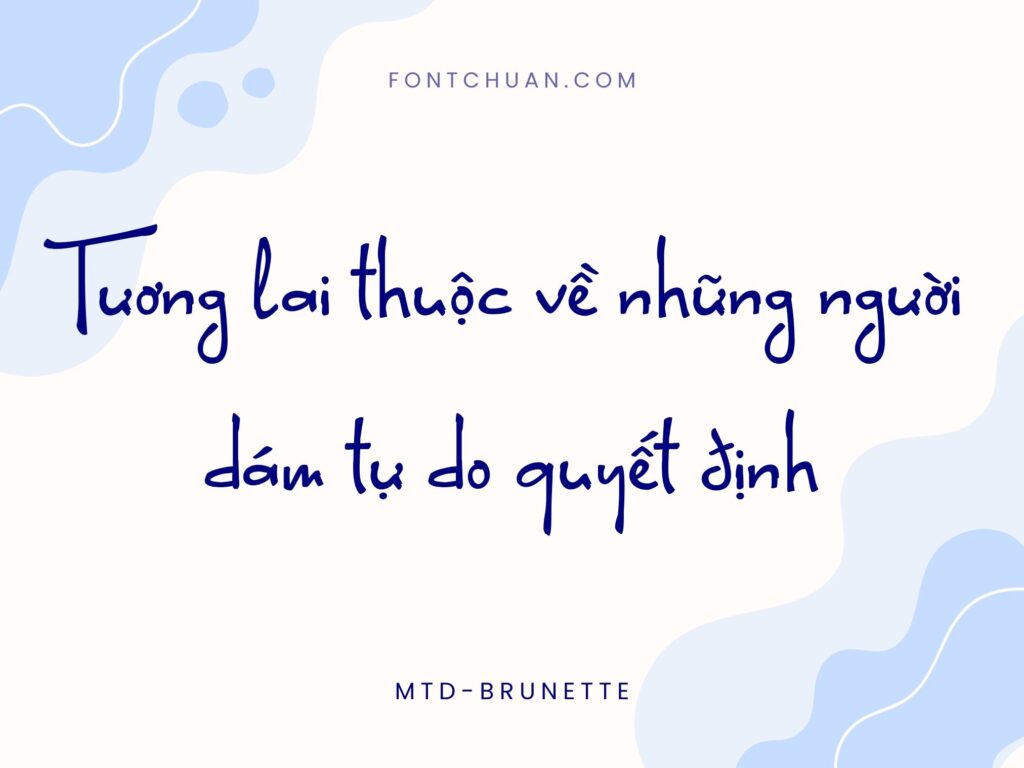
Font MTD Brunette Việt Hóa
Tác giả Font: Deartype
Font MTD Brunette là một kiểu chữ viết tay trang nhã, được thiết kế bởi DearType và Việt hóa bởi Mộc Hạ. Font này hỗ trợ đầy đủ tiếng Việt cùng hơn 90 ngôn ngữ khác, mở rộng khả năng ứng dụng trong các thiết kế đa ngôn ngữ. Đây là một trong những phông chữ được cộng đồng thiết kế đánh giá cao và sử dụng trong nhiều dự án sáng tạo, đáp ứng nhu cầu đa dạng của người dùng.
MTD Brunette nổi bật với các đường nét mềm mại và uyển chuyển, mang đến cảm giác thân thiện và gần gũi. Font rất phù hợp cho các thiết kế logo, tiêu đề, bao bì sản phẩm, thiệp mời và các ấn phẩm đòi hỏi sự tinh tế và nghệ thuật. Các ngành nghề phù hợp bao gồm quảng cáo, giáo dục, công nghệ, thiệp cưới và ảnh cưới. Font này cũng lý tưởng cho các sự kiện như Tết, Giáng sinh, Valentine và các lễ hội khác.